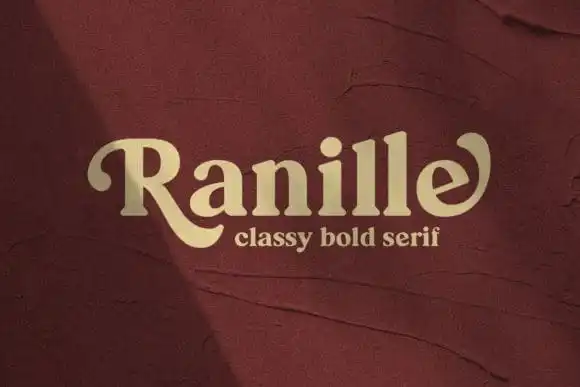
Ranille Serif Font é uma fonte serif moderna que traz um toque romântico, com uma grande variedade de alternativas que incluem terminais de bola. Esta elegante fonte oferece alternativas e ligaturas que a tornam perfeita para várias aplicações gráficas, desde criação de marca até assinatura e logotipo. Arterfak Project é o designer responsável por esta fantástica fonte, ideal para quem busca um estilo sofisticado e contemporâneo. Com alternativas de letras que criam um visual atraente, Ranille Serif Font pode transformar qualquer projeto em uma obra-prima de design. Seja para projetos de branding ou design editorial, invitations de aniversário ou até mesmo rótulos, essa fonte é perfeita para incrementar os mais diversos ambientes gráficos. Não hesite em experimentar Ranille Serif Font; ela certamente elevará seu próximo projeto ao nível superior.